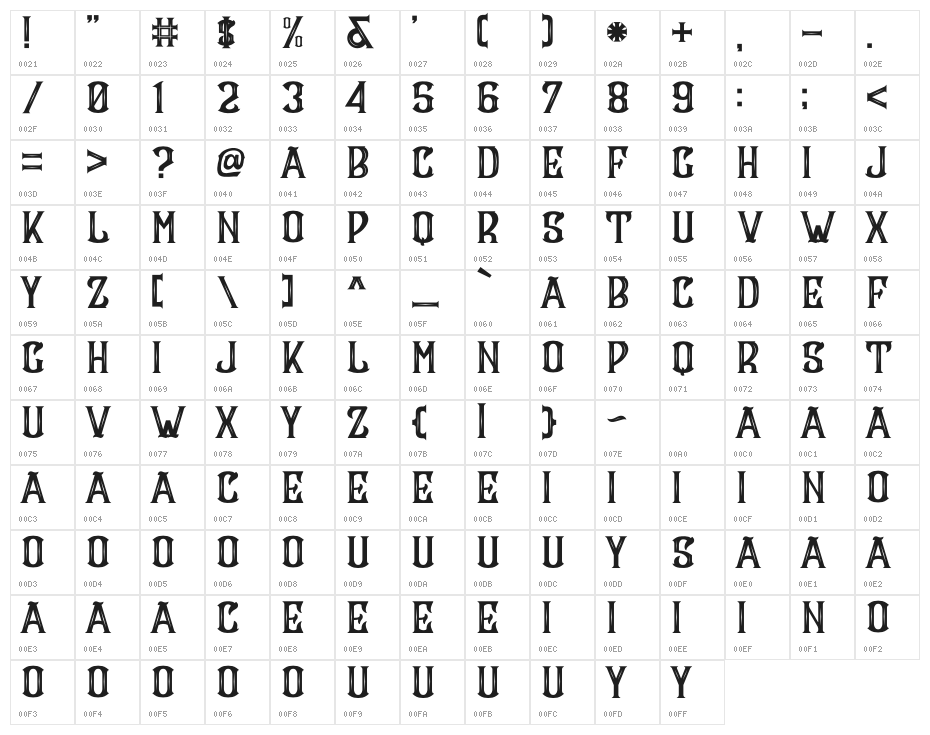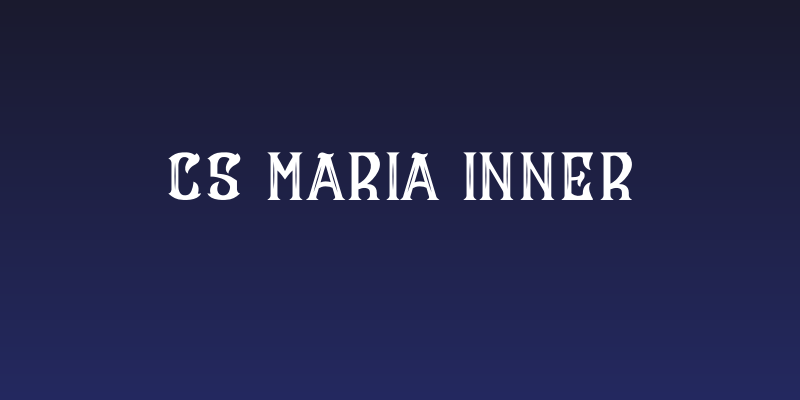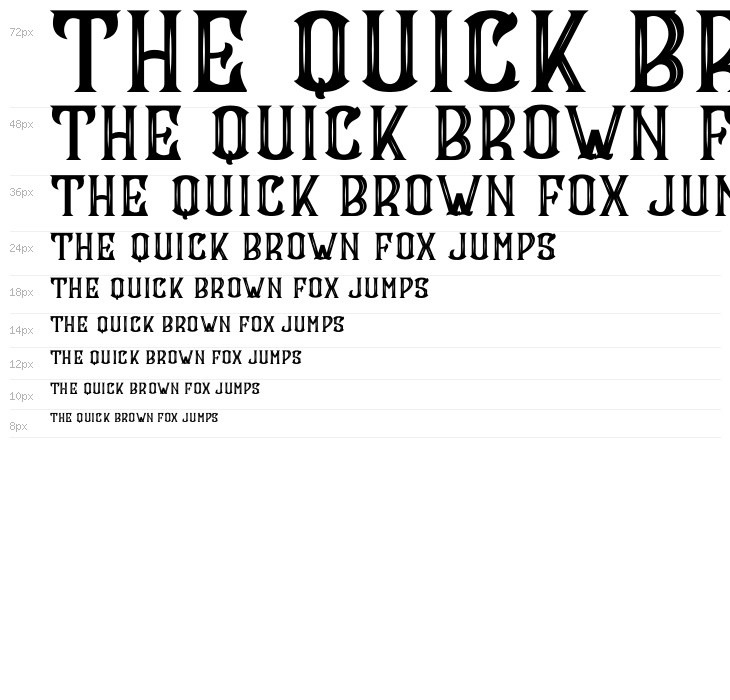
CS Maria Inner Font
| Gesamtstil | Modern Gothic |
| Vorgeschlagene Projekte | Ideal for use in branding, posters, album covers, and any project requiring a dramatic and bold typographic statement. |